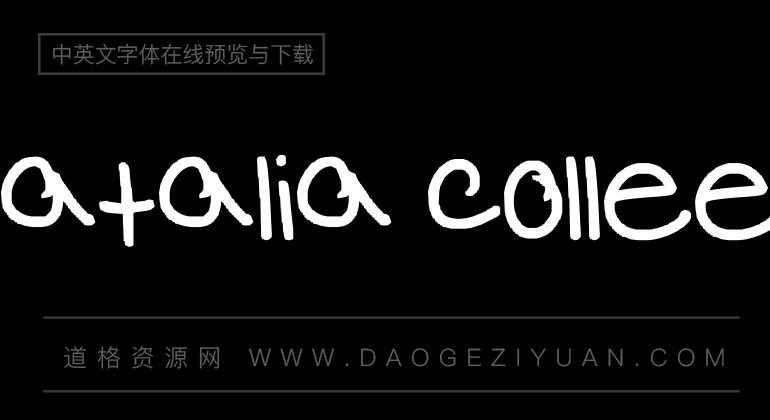
Natalia Colleen 字体是一款由 Natalia Colleen 设计的新字体,它是一款温柔优雅的英文字体,主要特点是字体有着柔和的曲线,让文字散发出温暖的气息。它是一款多功能字体,适用于各种商业应用,可以用于宣传单、标志、海报、品牌标识、广告等,是一款很好的英文字体。内容介绍
Natalia Colleen是一款非常不错的手写艺术字体,具有很好的视觉感,适合于文化类的宣传设计、商业类品牌的广告和产品包装设计以及个性化文字排版等较多场景。